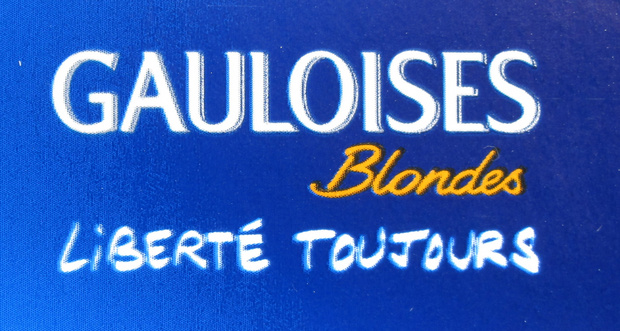
GAULOISES Schrift
ich bin auf der Suche nach den Schriften, die man auf der GAULOSIES Blondes Zigarettenschachtel findet.
Ich suche die Schriften des Wortes "GAULOISES", "BLONDES" und "LIBERTE TOUJOURS" (siehe angehängtes Bild).
Kennt jemand zufällig den Namen dieser Schriften oder kann mir ähnliche nennen?
"Liberté Toujours" ist ziemlich sicher handgezeichnet, schätze ich mal. Die Hanshand und die Juergen (beide von Hans J. Zinken) werden sehr gerne als "Ersatz" genommen.
Ich frag' nur der Form halber - hast du MyFonts bereits damit gefüttert?
Hatte leider bei MYFONTS keinen Erfolg, da die Schrift auf dem Foto doch sehr aufgerastert war. Auch beim MYFONTS Forum kam bisher noch kein Feedback.
Kennst du denn eine Schrift, die der GAULOISES Schrift ähnlich ist?
Wenn Du eine Originalschachtel hochauflösend einscannst hast Du vermutlich weniger Raster-Probleme bei Myfonts.
Wurden die Schriften identifiziert? Dann würde mich das Ergebnis interessieren.